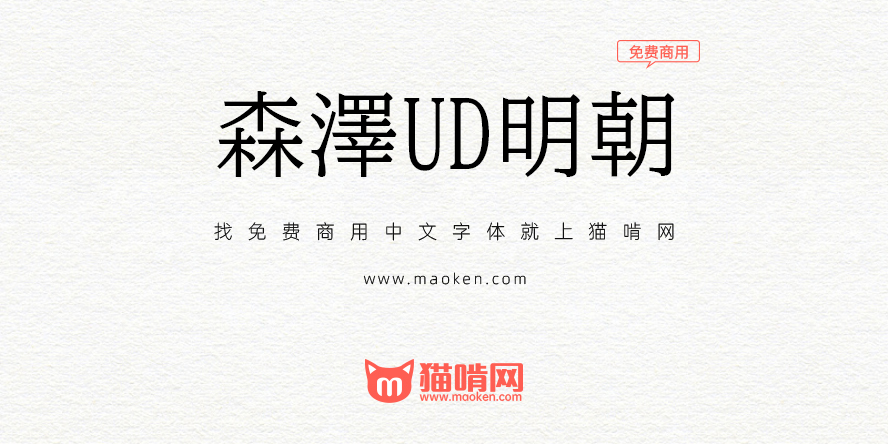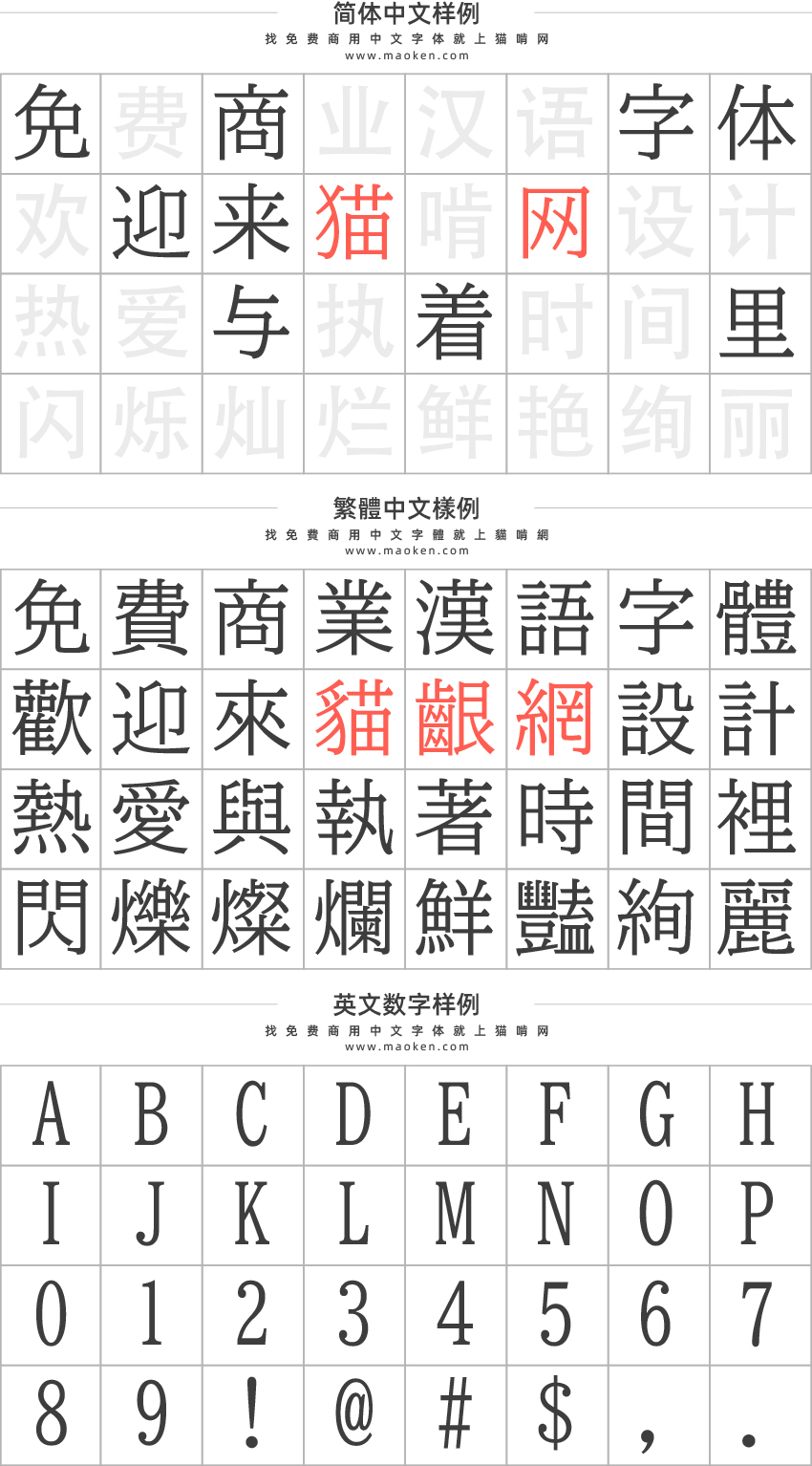
森泽UD明朝:结合力易于识别和易读性以及明朝字体的高级传统
字体作者:森泽株式会社 (日本) 字体字重:2个
森泽 UD 明朝结合了易于识别和易读性以及 Mincho 字体的高级传统。由于大多数 Mincho 类型的设计都带有精细的水平线条,因此某些显示和标志对于有视力问题的人来说难以阅读。“TypeBank UD Mincho”是在“TypeBank Yoko Futo (Bold Horizo​​ntal) Mincho”的基础上设计的,水平线条比传统的 Mincho 字体更粗。对于通用设计版本,响音和半响音符号设计用于更容易识别,并且调整了字符以保持其形状,具有略大的字面和更宽的中宫。
• 添加了 UD Mincho 和 UD PMincho 的新权重(粗体)。
• 字形集已扩展为以下字符:
• Ċ Đ Ĕ Ė Ğ Ģ Ġ Ħ IJ Ĭ İ Į Ĩ Ķ Ļ Ŀ Ÿ Ŋ Ŏ Ŗ Ŧ Ų Ũ Ŵ Ŷ Ÿ ċ ĕ ė ğ ģ ġ ı ĭ ij į ĩ ķ ĸ Ō ŗ ŵ Ō ņ ņ ŷ fi FL Ѓ Ґ Ќ Ў Џ Љ Њ Ѕ Є І Ї Ј Ћ Ђ ѓ ґ ќ ў џ љ њ ѕ є і ї ј ћ ђ Ά Έ Ή Ί ΰ Ύ Ώ Ϋ ϋ ή ΐ ύ ⁴ ⁄ ‚ „ ‹ › ƒ ≥ ≤ ∏ µ ◊ ™ ^ ˚ ΄ ΅
• 此外,反斜杠字形已从 JIS 标准日元形式交换为 Unicode 标准反斜杠字形。
• 添加了其他字符以满足 Google 字体的核心拉丁字形集。